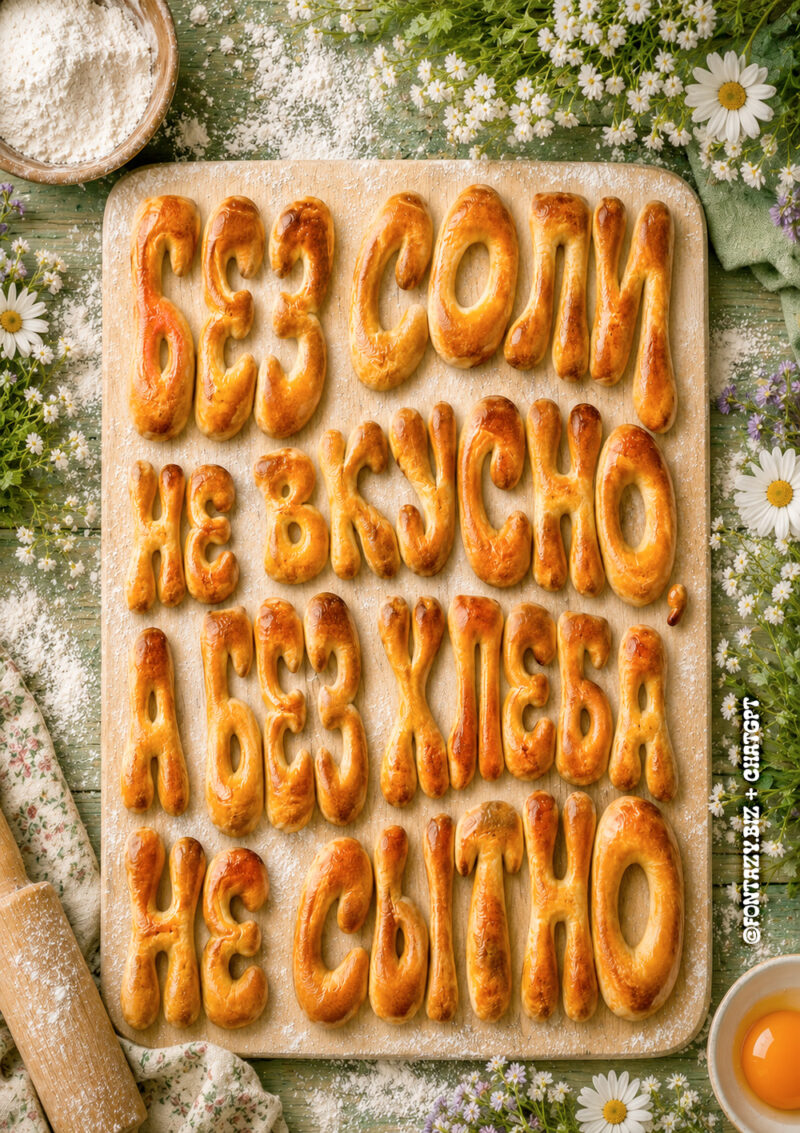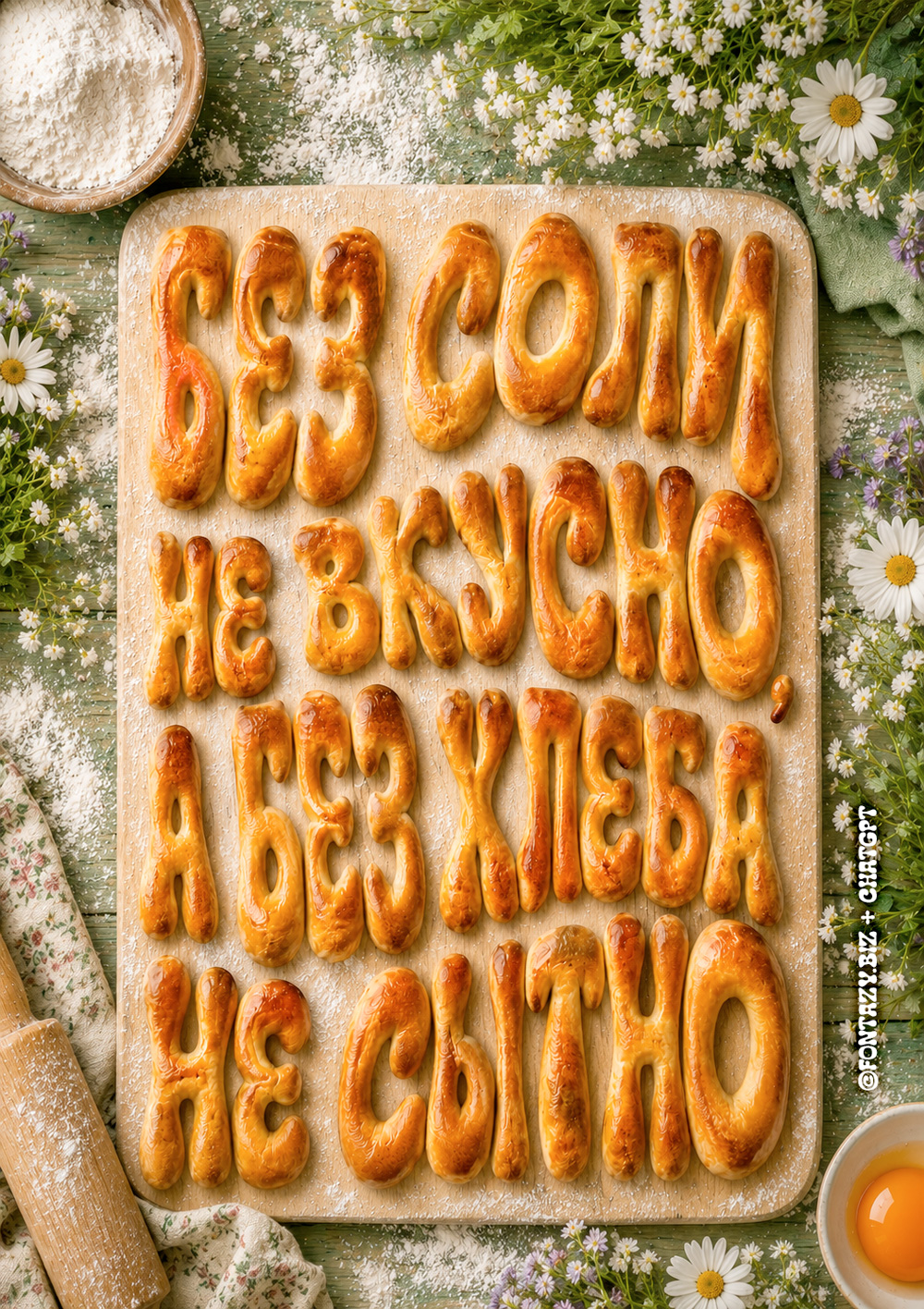
Без хлеба
Готовлю одну интересную штучку и в процессе подготовки сделал плакатик с пословицей.
ЧатЖПТ жжот! Точнее, печёт. А буковки мои и мне они очень нравятся!
Шрифтовой исходник. Использован мой шрифт Тесто.